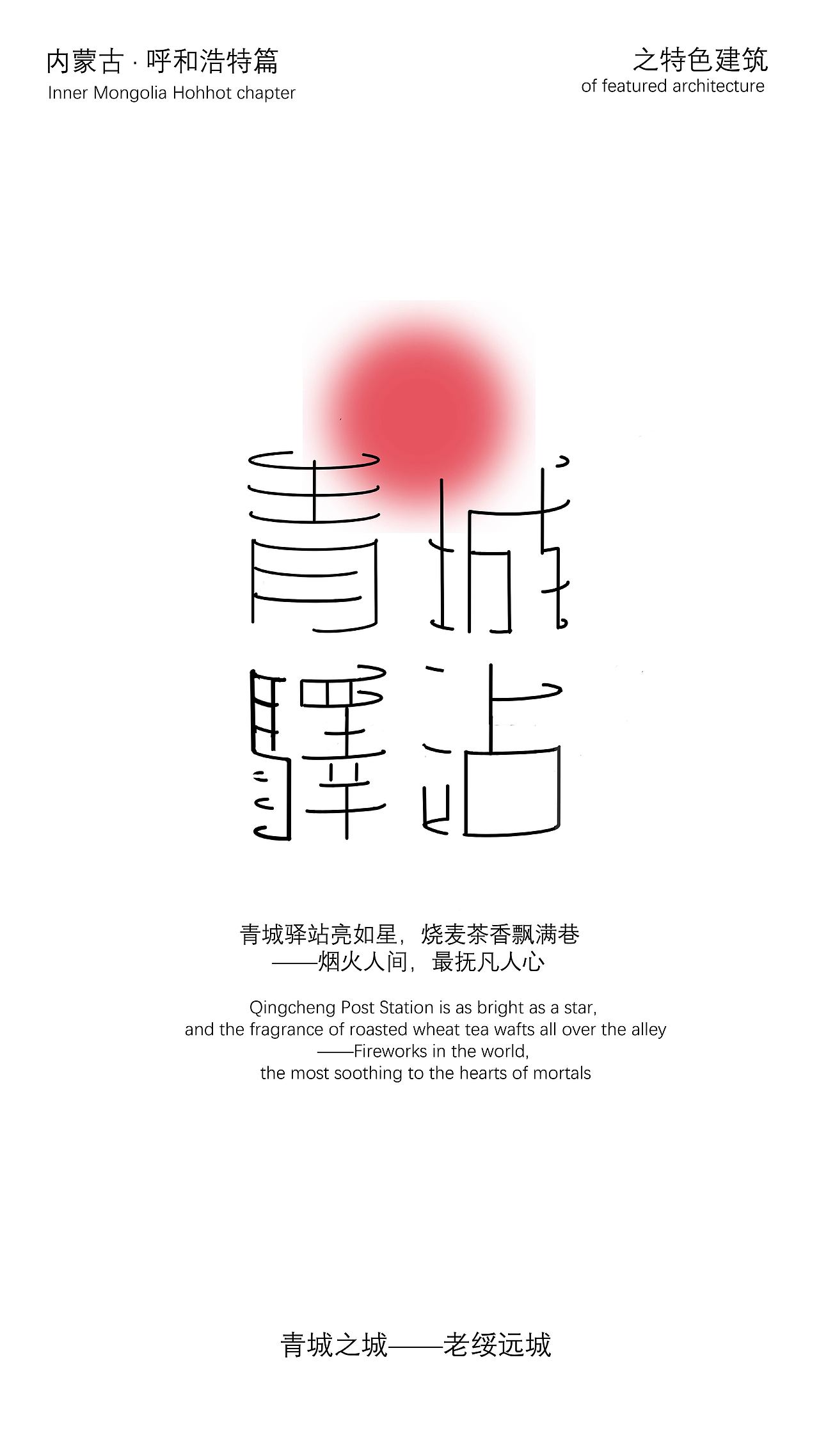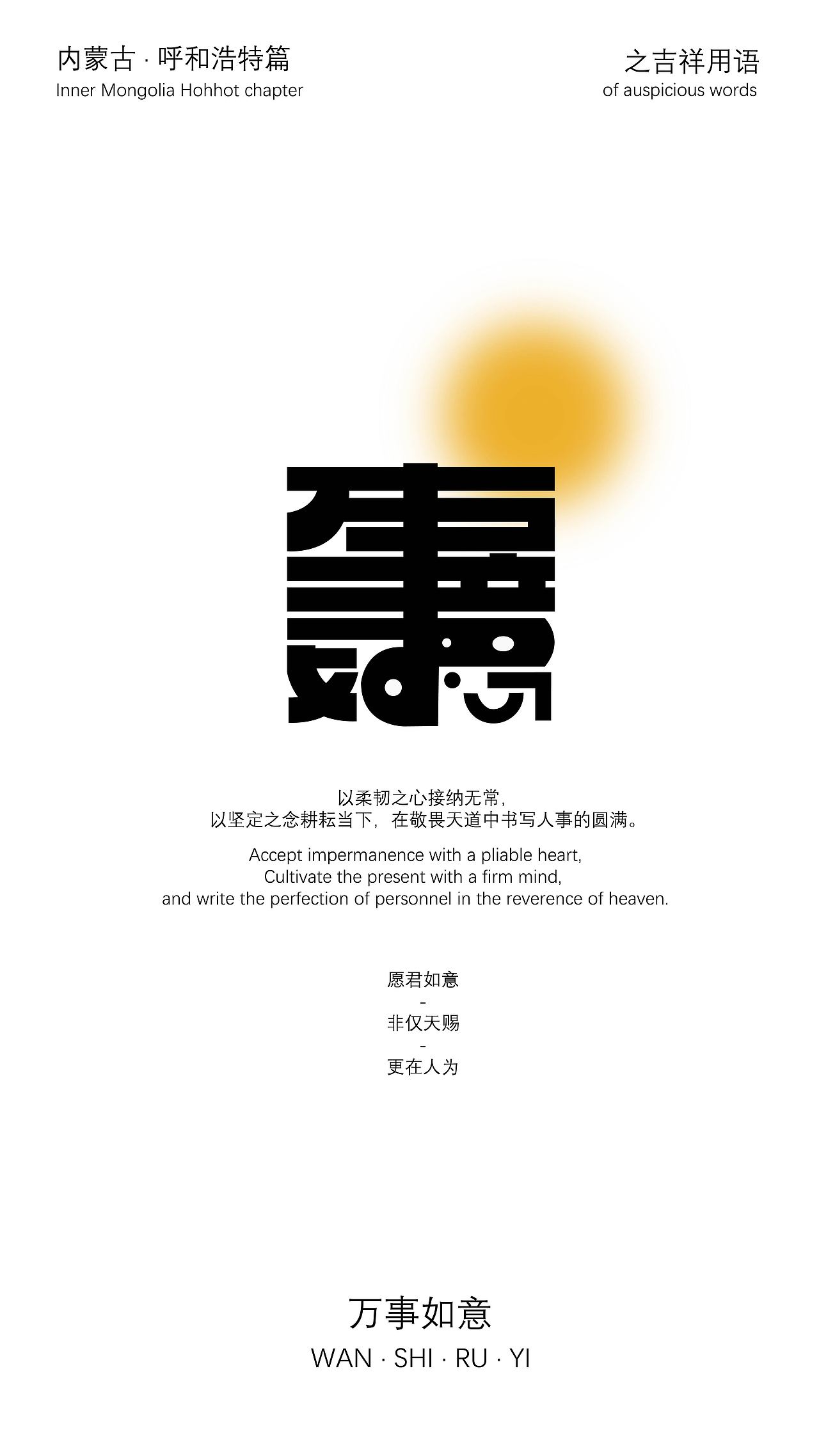
呼和·形态——基于呼和浩特主题字体设计
设计理念:
选取内蒙古呼和浩特特色的文化、美食,旅游景点,民族特色等 为主内容进行字体设计用线条构建一座「行走的青城」—— 让字体成为可阅读的文化地标。静态设计阶段,以“个性魅力"“善连善断““具象抽象”“点线面的应用”“点晴与添足”增减合并共用“格律文字设计”为主题设计字体。